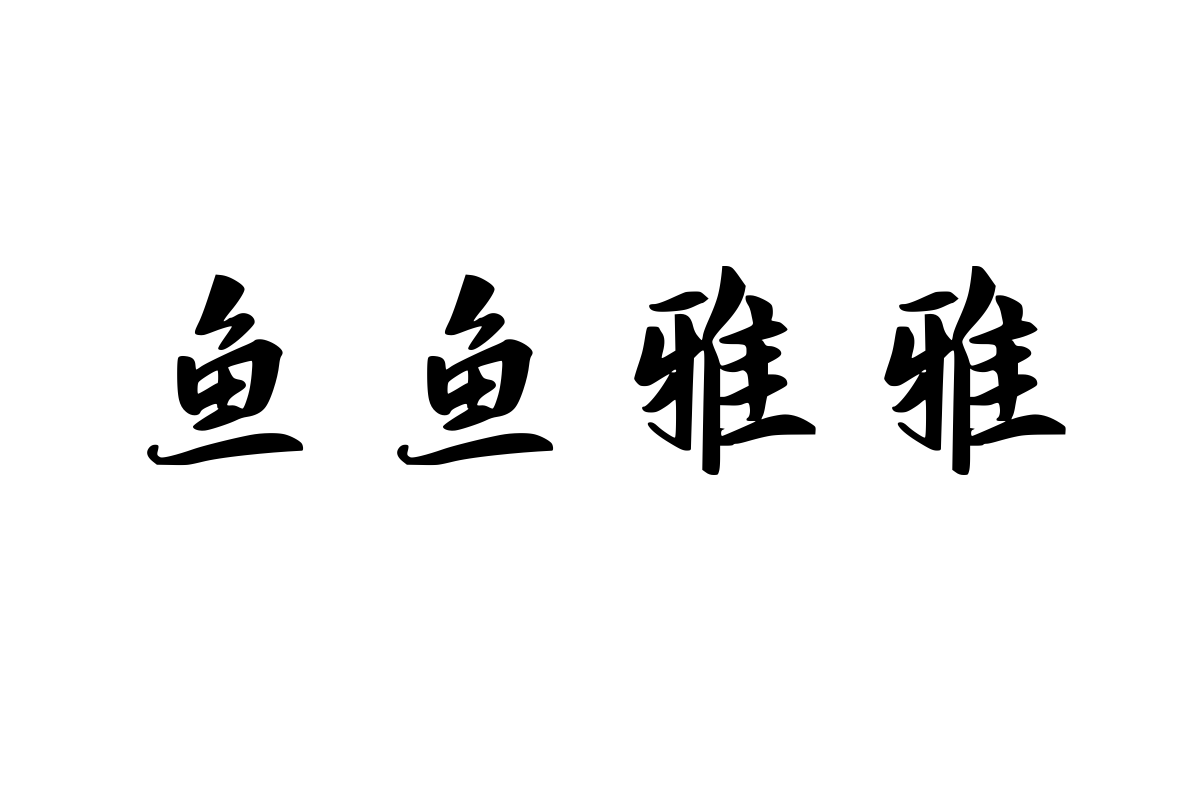
兰米静心粗行楷是一套由中国书法家兰米创作的行楷字体。这套字体以其独特的风格和特点而受到广泛赞誉,被广泛应用于各种印刷品、广告、设计等领域。
兰米静心粗行楷的特点如下:
1. 笔画流畅:兰米静心粗行楷的笔画流畅自然,线条粗细适中,给人一种舒适的感觉。
2. 结构紧凑:这套字体的结构紧凑,每个字都保持了一定的空间感,使得整体布局更加和谐。
3. 字形饱满:兰米静心粗行楷的字形饱满,每个字都有充足的空间,使得整体效果更加美观。
4. 易于识别:兰米静心粗行楷的字形简洁明了,容易识别,方便人们阅读。
5. 适用范围广泛:兰米静心粗行楷适用于各种场合,无论是在印刷品、广告、设计等领域,都能发挥其独特的魅力。